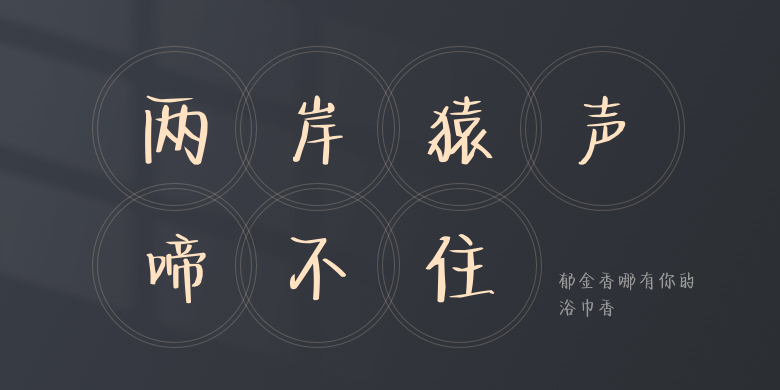
郁金香哪有你的浴巾香
郁金香哪有你的浴巾香,这款字体结构工整、笔画清晰,兼顾美观与易读性,适用于标题、正文、海报、包装、LOGO 等多种场景。字形优雅稳定,风格百搭耐看,适配日常排版与创意设计,让文字呈现更舒适、更具质感。郁金香哪有你的浴巾香一笔一画,皆是细节,以均衡的比例、流畅的线条打造舒适视觉体验,字形端正大气,风格简约现代。无论是商业设计、品牌宣传还是日常排版,都能轻松驾驭,让文字更有格调与力量。郁金香哪有你的浴巾香字体下载。